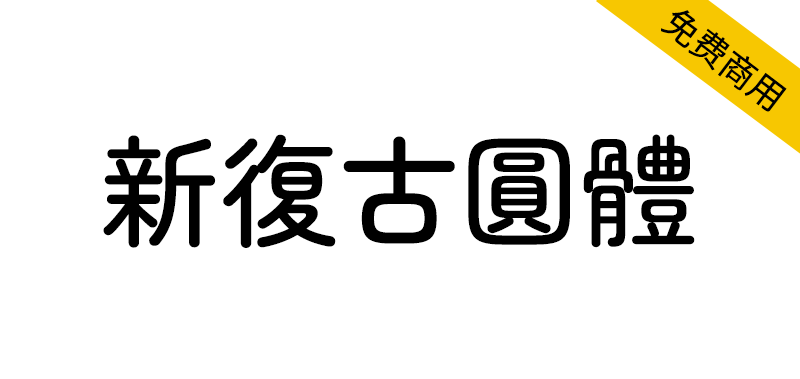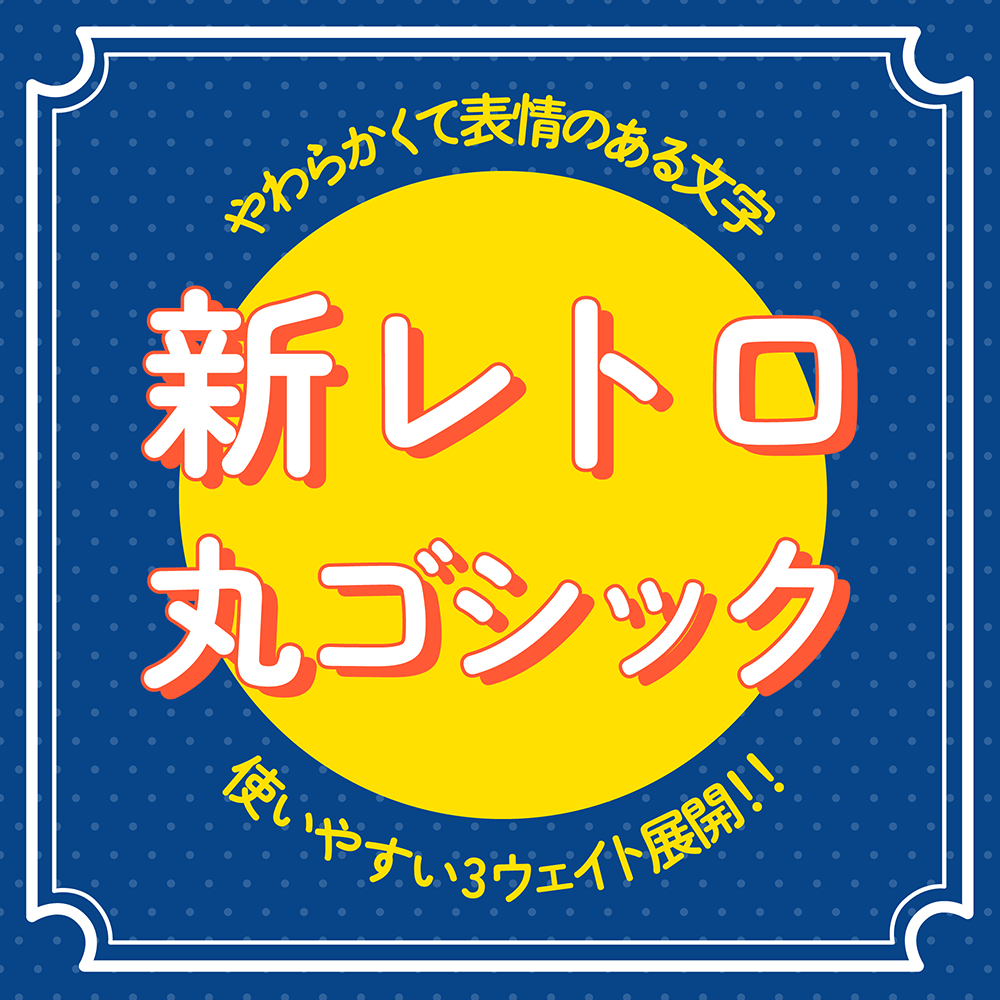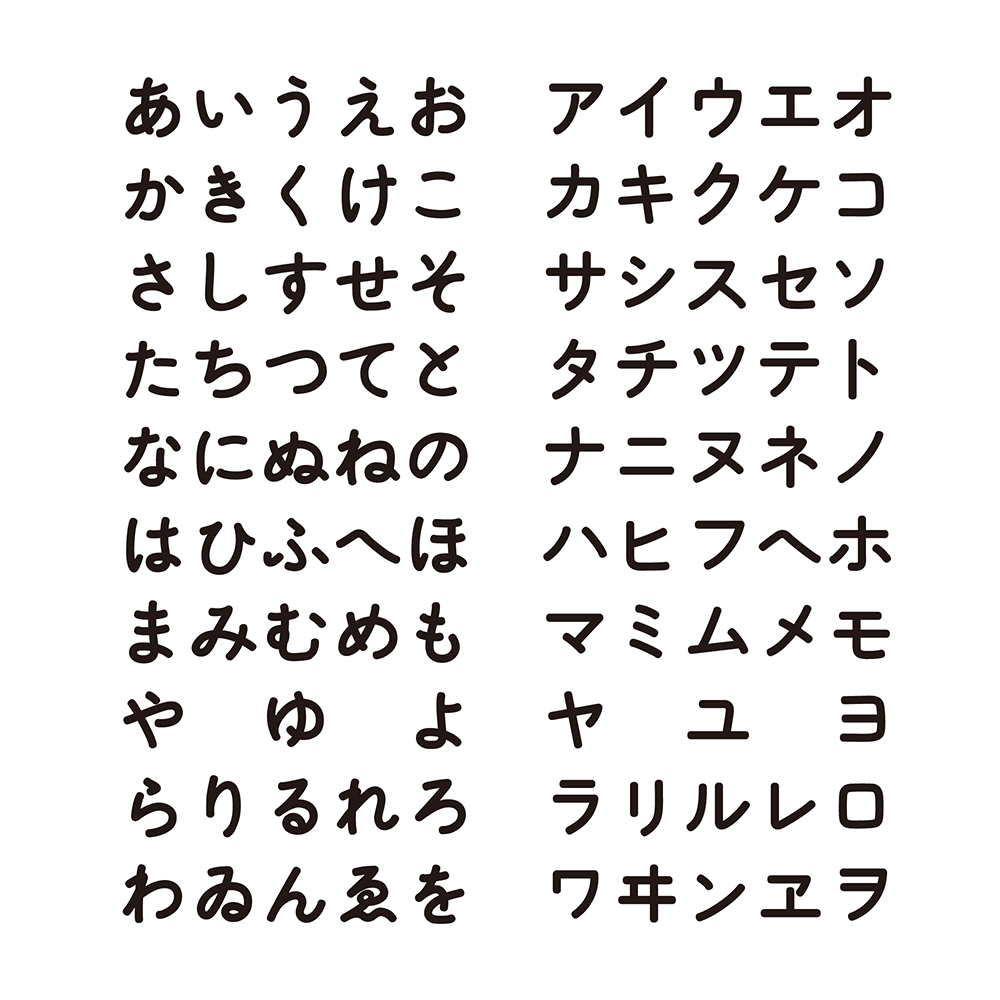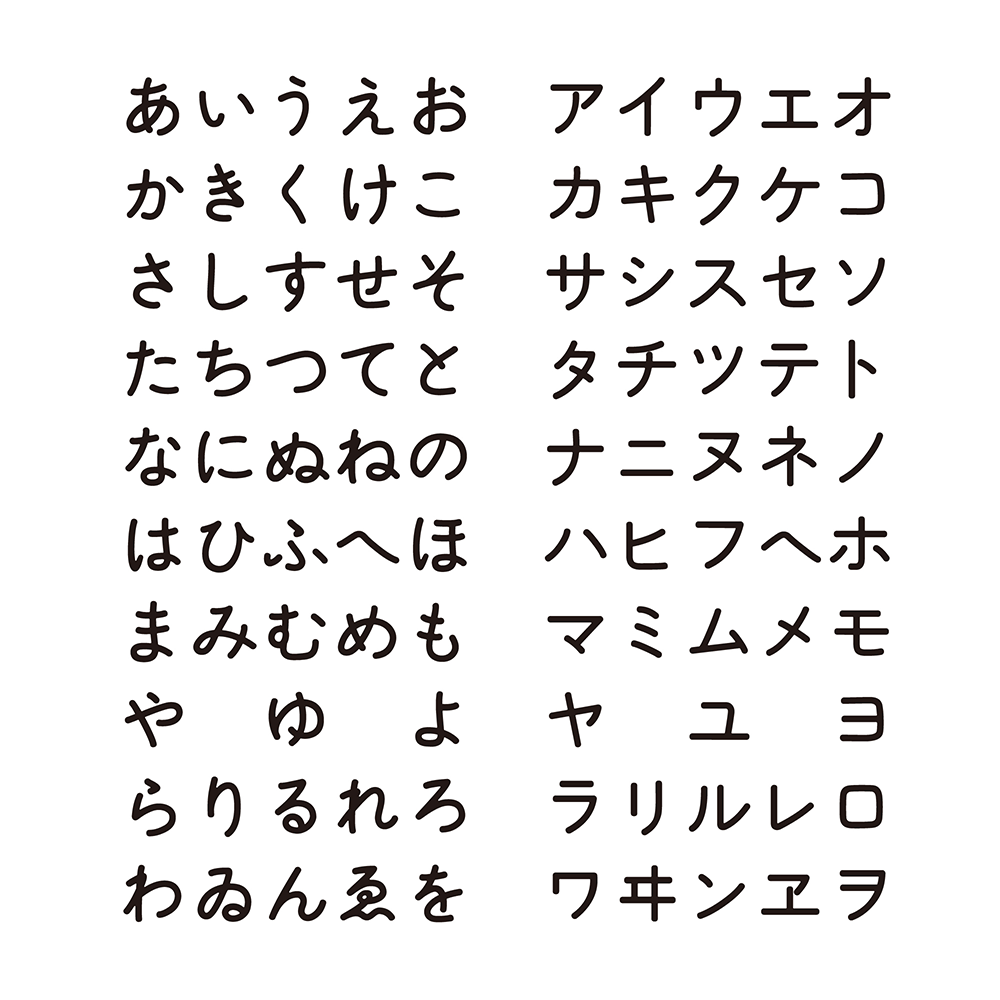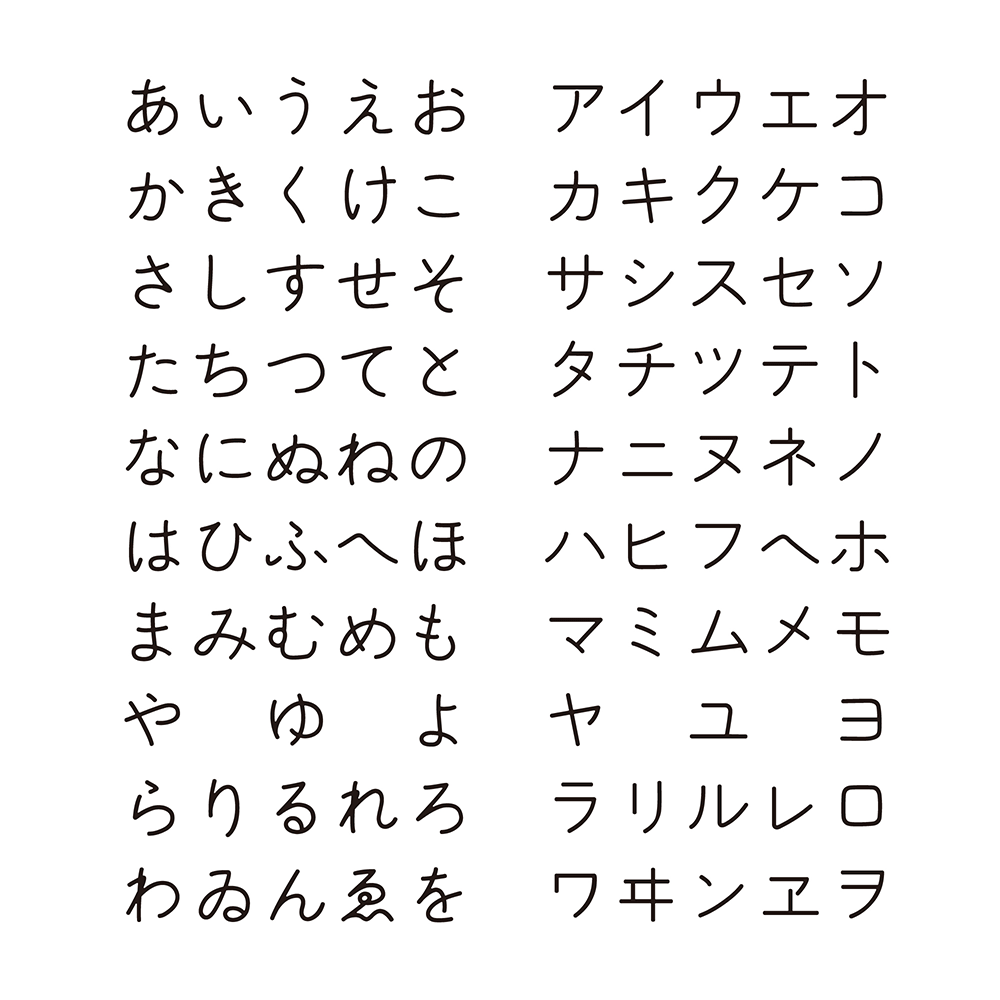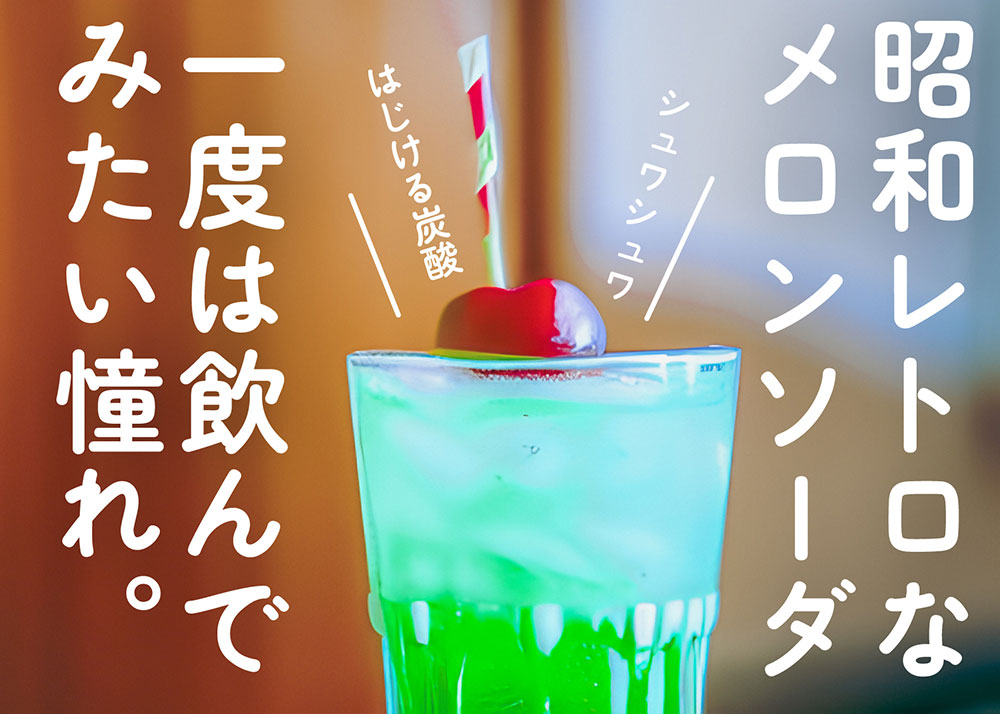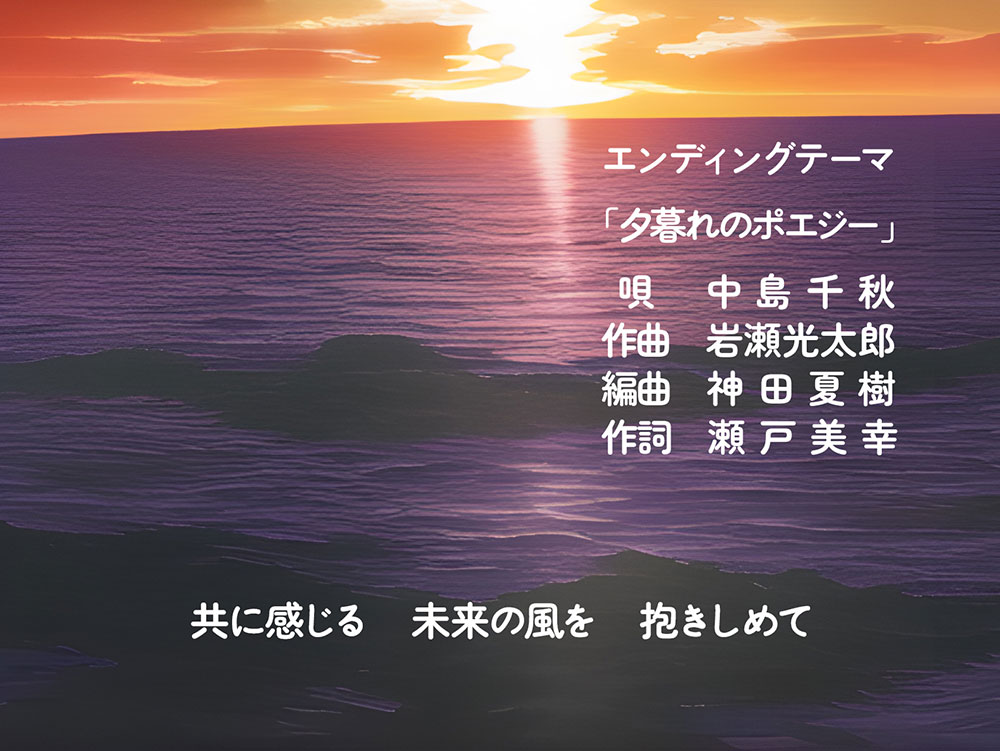
新复古圆体(新レトロ丸ゴシック)是参考了20世纪日本使用照相排版技术时期(1960-1990年代)使用的圆形黑体而制作的。柔和而富有表现力的假名,能很好地还原昭和至平成时期印刷品及电视字幕的怀旧氛围。其中「と」字的第一笔划突破常规的设计尤为特色。该字体提供Regular、Medium、Bold三种易用的字重,适用范围广泛,从标题到正文均可胜任。除假名和部分标点符号外,其余字符沿用自「ZEN丸ゴシック」。此外,在制作过程中,我们特别感谢字体赞歌(@typeface_anthem)提供的资料支持,并对原始字体开发者致以深切谢意。
新レトロ丸ゴシックは写植時代に使われていた丸ゴシックを参考に作られました。懐が狭めで表情のある柔らかな仮名は、昭和~平成の印刷物やテレビのテロップ雰囲気を出すのに似合うはずです。特に一画目が突き抜けた「と」のデザインが特徴的です。ウェイトは使いやすいRegular、Medium、Bold三種類で見出しから本文まで幅広く使用できます。かなと一部約物を除き「ZEN丸ゴシック」から利用しています。また、制作にあたり情報の提供をいただきした、書体讃歌(@typeface_anthem)さんとオリジナルのフォントに深く感謝いたします。